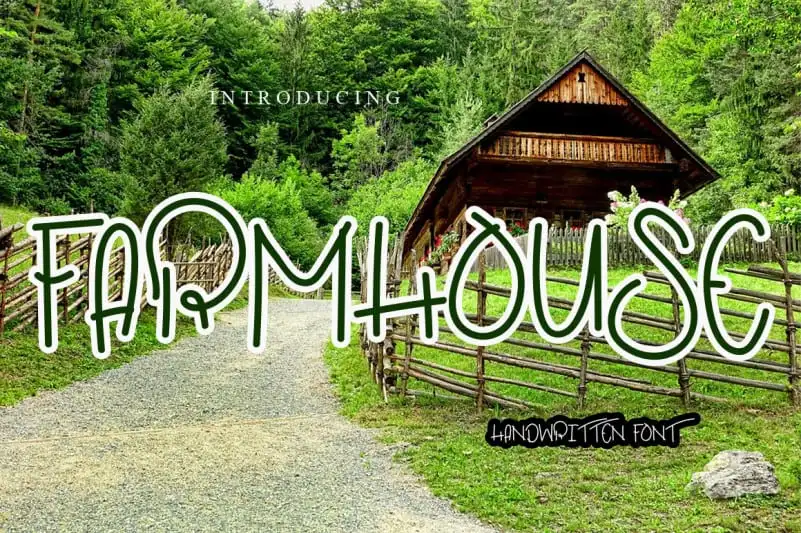
Farmhouse Handwritten Font – Download Grátis
A Farmhouse Handwritten Font é uma elegante escolha para quem busca uma tipografia que transmite simplicidade e leveza ao mesmo tempo. Uma vez impressa no design, essa fonte de escrita manuscrita se destaca por sua versatilidade impressionante, capaz de dar vida a um amplo range de trabalhos gráficos. Perfeita para quem busca uma personalidade única em cada projeto, esta fonte é ideal para aqueles desejando criar designs que expressam calma e simplicidade. Seja em postais familiares, revistas ou até mesmo cartões-de-árabe de celebração, a Farmhouse Handwritten Font tem o poder de dar um toque único à qualquer trabalho gráfico. Não importa qual seja o objetivo do seu projeto, essa fonte manuscrita pode contribuir para eleger seus designs para um novo patamar, tornando-os ainda mais autênticos e convidativos.